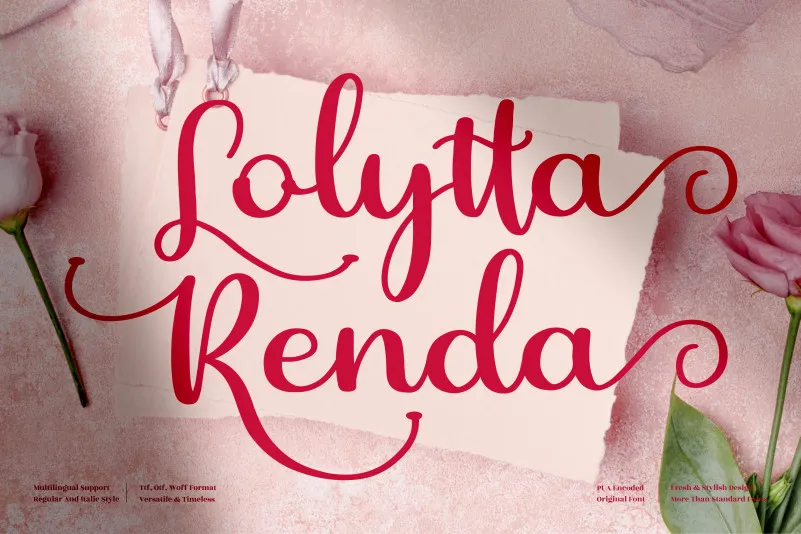
A Lolytta Renda Font é uma elegante caligrafia que se destaca por sua graça e delicadeza perfeita para diversas aplicações visuais, desde a criação de logotipos até as embalagens de produtos. Seu formato suave e arredondado é especialmente adequado para designs de roupas, como etiquetas de shopping, cartões de nome, convites de aniversário, enfeites de foto, e mesmo para gráficos e assinaturas. Com sua natureza romântica e sofisticada, a Lolytta Renda font é perfeitamente adaptável às necessidades dos profissionais que desejam dar um toque encantador às suas criações. Além disso, o designer perspectype trouxe uma combinação única de elegância e originalidade para esta caligrafia, garantindo que a Lolytta Renda font seja uma escolha inegável tanto para iniciantes quanto para profissionais ávidos por novas ideias e designs.